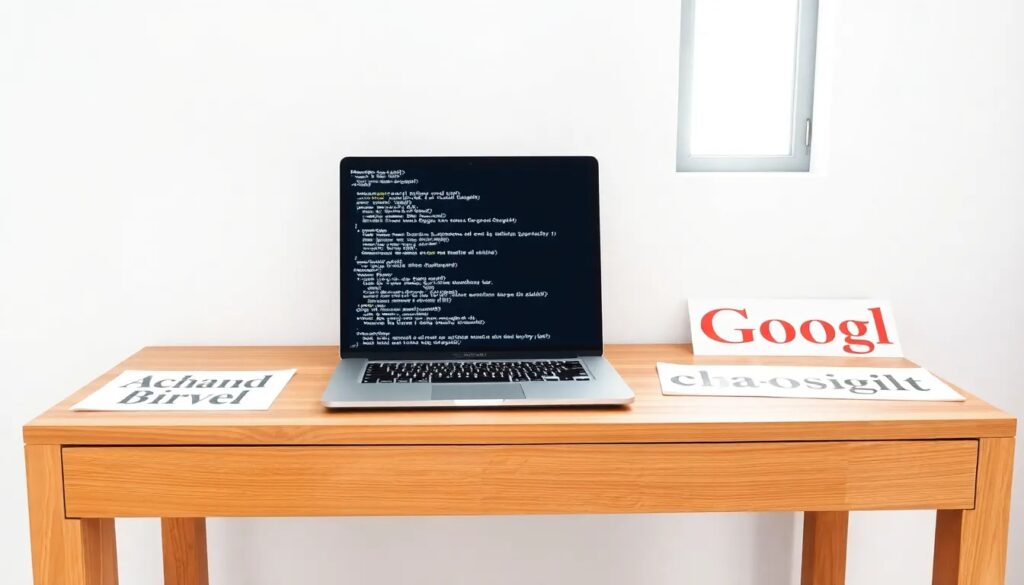
Google font css: cómo usarlas en tu sitio web
La tipografía es un aspecto fundamental en el diseño web, y Google Fonts se ha convertido en una herramienta imprescindible para personalizar la apariencia de nuestros sitios. Esta plataforma ofrece una amplia variedad de fuentes que pueden ser fácilmente integradas en cualquier proyecto.
En este artículo, exploraremos todo lo que necesitas saber sobre google font css, desde cómo utilizarlas hasta consejos para optimizar su uso. ¡Acompáñanos en este recorrido por el fascinante mundo de las tipografías!
¿Qué son las fuentes Google?
Las fuentes Google son un servicio gratuito que proporciona acceso a más de 1000 tipografías personalizables. Estas fuentes son ideales para dar un toque único a cualquier página web y mejorar la experiencia del usuario.
La principal ventaja de utilizar Google Fonts es su facilidad de uso. Disponibles en formato web, solo necesitas incluir un enlace en tu código HTML para comenzar a usarlas. Esto permite una integración rápida y eficiente, facilitando así el proceso de diseño.
Además, las fuentes están optimizadas para la web, lo que asegura que se carguen de manera rápida y adecuada en cualquier dispositivo. Esto es esencial, ya que una carga lenta puede afectar la experiencia del usuario y el rendimiento del sitio.
¿Cómo usar Google Fonts en tu proyecto web?
Integrar Google Fonts en tu proyecto es un proceso sencillo. A continuación, te explicamos cómo hacerlo paso a paso:
- Visita el sitio web de Google Fonts y selecciona las fuentes que deseas utilizar.
- Haz clic en "Seleccionar esta fuente" y personaliza las opciones según tus necesidades.
- Copia el enlace proporcionado y pégalo en la sección <head> de tu archivo HTML.
- En tu archivo CSS, utiliza la propiedad font-family para aplicar la fuente a los elementos deseados.
Siguiendo estos pasos, podrás incorporar fácilmente fuentes personalizadas en tu diseño. Recuerda que puedes combinar múltiples fuentes utilizando el carácter '|'. Sin embargo, es recomendable no abusar de esto, ya que puede afectar la carga de la página.
¿Cuáles son las mejores fuentes de Google?
La elección de la fuente adecuada puede transformar el aspecto visual de tu sitio web. Algunas de las mejores fuentes de Google que se destacan son:
- Roboto: Perfecta para interfaces modernas, es muy legible en pantallas.
- Open Sans: Ideal para textos largos, ofrece una excelente legibilidad.
- Lato: Su diseño limpio y contemporáneo la hace muy versátil.
- Montserrat: Una fuente geométrica que da un toque moderno y atractivo.
- Raleway: Perfecta para encabezados gracias a su estilo elegante.
Al seleccionar una fuente, considera la personalidad de tu marca y el mensaje que deseas comunicar. Utilizar tipografías adecuadas puede hacer que tu sitio destaque entre la competencia.
¿Cómo estilizar fuentes de Google con CSS?
Las opciones de estilización que te ofrece google font css son vastas. Puedes aplicar diferentes propiedades para mejorar la apariencia de tus textos. Aquí algunos ejemplos:
- font-weight: Para definir el grosor de la fuente.
- font-style: Utiliza esta propiedad para aplicar cursiva.
- text-shadow: Agrega sombras a los textos para dar profundidad.
Además, puedes crear efectos visuales más complejos combinando varias propiedades. Por ejemplo, puedes aplicar una sombra de texto junto con un tamaño de fuente diferente para resaltar ciertos elementos dentro de tu sitio.
¿Qué es la API de Google Fonts y cómo funciona?
La API de Google Fonts permite a los desarrolladores acceder a las fuentes de manera dinámica. Esta API es especialmente útil para proyectos donde se requiere una mayor flexibilidad. Aquí te explicamos cómo funciona:
Utilizando la API, puedes solicitar fuentes específicas a través de un enlace. Por ejemplo, puedes especificar el peso y estilo que necesitas. Esto optimiza la carga, ya que solo se descargan las fuentes requeridas.
Además, la API permite la integración de fuentes variables, que ofrecen un rango de estilos en una sola fuente. Esto no solo ahorra espacio, sino que también mejora el rendimiento del sitio.
¿Cómo optimizar el uso de Google Fonts para mejores cargas?
La optimización es clave para asegurar que tu sitio se cargue rápidamente. Aquí algunos consejos para mejorar la velocidad al usar Google Fonts:
- Selecciona solo las fuentes que realmente necesitas.
- Utiliza la opción de preconexión en tu enlace para mejorar los tiempos de carga.
- Evita cargar múltiples variantes de una misma fuente a menos que sea necesario.
- Configura el parámetro text= en tu enlace para limitar los caracteres solicitados.
Implementar estas prácticas no solo mejorará la velocidad de tu sitio, sino que también contribuirá a una mejor experiencia para tus usuarios.
¿Puedo usar varias fuentes de Google en un solo proyecto?
¡Sí! Utilizar varias fuentes de Google en un solo proyecto es completamente posible y puede enriquecer tu diseño. Sin embargo, es importante hacerlo de manera responsable:
Cuando combines múltiples fuentes, asegúrate de que sean complementarias y mantengan la coherencia visual. Por ejemplo, puedes usar una fuente para los encabezados y otra para el cuerpo del texto. Esto puede ayudar a crear jerarquía y guía visual en la página.
Recuerda también que cada fuente que añadas puede aumentar el tiempo de carga de la página, por lo que es recomendable medir el impacto de cada fuente en el rendimiento general del sitio.
Finalmente, no olvides agregar una fuente de respaldo en caso de que alguna fuente no se cargue correctamente. Las fuentes como serif o sans-serif son buenas opciones para esto.
Preguntas frecuentes sobre Google Fonts
A continuación, respondemos algunas de las preguntas más comunes sobre el uso de Google Fonts:
- ¿Qué son las fuentes Google? Son tipografías que se pueden utilizar de forma gratuita en sitios web.
- ¿Cómo usar Google Fonts en mi proyecto web? Solo necesitas incluir un enlace en el HTML y referenciar la fuente en CSS.
- ¿Cuáles son las mejores fuentes de Google? Fuentes como Roboto, Open Sans y Montserrat son muy populares y versátiles.
- ¿Cómo estilizar fuentes de Google con CSS? Puedes aplicar propiedades como font-weight, font-style y text-shadow.
- ¿Qué es la API de Google Fonts y cómo funciona? Permite acceder a fuentes de manera dinámica y optimizada.
- ¿Cómo optimizar el uso de Google Fonts para mejores cargas? Selecciona solo las fuentes necesarias y utiliza preconexión.
- ¿Puedo usar varias fuentes de Google en un solo proyecto? Sí, pero es recomendable mantener la coherencia visual y cuidar la carga de la página.